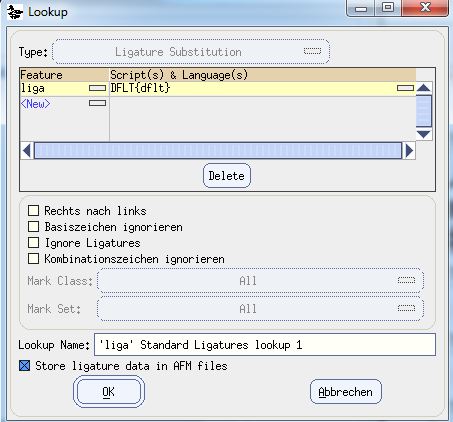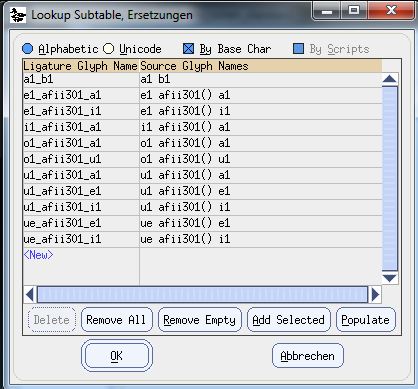
Frage zu Ligaturen/Ersetzungen
Aber wo wir und hier für die Wiederbeschäftigung unterbeschäftigter Buchstaben einsetzen. auch das y hatte damals - also in der Zeit mit dem u/v-Regel-Ding weit mehr Verwendung. Damals wurde es ja für den Ungerundeter geschlossener Hinterzungenvokal verwendet, der dann ber auch als 2. Teil des diphthonge ei auftaucht, und demzufolge konsequent ey geschrieben wurde.
Das ist kein sprachliches Problem, sondern ein rein Orthografisches.
Das die deutsche Sprache überhaupt noch in der Lage ist, solche einfachen Wortverbindungen aufzubauen, sollte als eine Gabe gesehen werden, die in vielen westlichen Sprachen schon verloren gegangen ist.
Zumindest in den anderen germanischen Sprachen funktioniert das genauso gut wie im Deutschen. Im Englischen verhȧlt es sich debei nur so, dass die verbundenen Wörter nicht auch noch verbunden geschrieben werden. Abgesehen von diesem orthographischen Unterschied funktioniert aber die englische Wortverbindung genau gleich wie im Deutschen.
Warum "Wachs" nicht "Wax" geschrieben wird (wie es auch der Aussprache entspricht), versteh ich nun überhaupt nicht,... wenn nun schon ein x im Alphabet vorhanden ist... sollte dieses auch genutzt werden.
Bei uns ist die Aussprache mit CH und S völlig normal.
nun habe ich das Problem, dass die Schriftdatei die Ligatur-Funktionen nicht auf die Schriftzeichen im "Private Use Zone" bezieht.
Die Ersetzungen an sich funktionieren, jedoch nur, wenn "lateinische Buchstaben" ersetzt werden sollen;
Nun befinden sich jedoch die Schriftzeichen - einschließlich aller Grundlaute - im privaten/ unbelegten Unicodebereich. Über ein eigens hierfür kreiertes zweites deutsches Tastaturlayout (für Windoof) können die Schriftzeichen eingegeben werden. Die Namen der einzelnen Glyphen im "PUA" der Schriftdatei sind die lateinischen Entsprechungen, wobei über eine angehängte Ziffer eine Verwechslung mit den Namen der Gylphen im Unicode-Block "Latin" ausgeschlossen werden soll.
beispielsweise wird der "f"-Laut in der "Private Use Zone" als "f1" bezeichnet (um eine Verwechslung mit dem lateinischen "f" auszuschließen).
Problem ist nun, dass die Ersetzungen (beispielsweise in Abiword) nicht funktionieren; aber sehr wohl, wenn ich meinen ersten Entwurf nehme, wo sich alle Schriftzeichen noch im lateinischen Unicod-Block zugeordnet befinden.
Ich denke, das Problem hat nichts mit dem zweiten Tastaturlayout zu tun, sondern ist ein Zuordnungsproblem im Schriftfont; vielleicht muss noch irgendwo angegeben werden, auf welchen Bereich sich die "Ligaturen" (bzw. allg. Ersetzungen) beziehen?...
Anbei drei Bilder zu den von mir betätigten Optionen...
Im 3. Bild sind die gegenwärtigen Ersetzungen zu sehen (der große Rest folgt später).
Die erste "Ligatur" ist die "ab"-Silbe, die nachfolgenden Reihen sind verschiedene Zwielaute (für diverse Dialekte), die mithilfe des Nullbreitenzeichen über die Tastatur ermöglichst werden sollen.
Allg. zur Schrift: das "Projekt" ist eine Lautschrift für die Deutsche Sprache, bzw. eine, die alltagstauglich, d.h. möglichst logisch- und einfach strukturiert ist, und dennoch eindeutig und exakt die Wörter so darstellt, wie diese auch ausgesprochen werden.
auch existieren für ALLE Laute (bsp. "ng", "ch", "sch", "pf" usw..) eindeutige Schriftzeichen, weshalb die Wörter extrem stark entschlackt, kürzer geschrieben werden als im lateinischen Alphabet.
Insgesamt sind es 47 Grundlaute / Grundbuchstaben. Diese sind dann noch systematisch untereinander kombiniert:
1. die Konsonanten untereinander, z.B. "tsch", "schr", "schp" (wie in "sp-ielen"), ngk (wie in "Da-n[g]k), "fr", "lz", "nft" (wie in Zuku-nft") usw...)
(insgesamt ca. 300 solcher "Verknüpfungen"; aber diese sind sehr sehr sehr leicht zu merken, da extrem systematisch, sodass tatsächlich nur um die 100 neue Zeichen erstellt werden müssen);
2. Silben (aber nur "Vokal oder Zwielaut + Konsonant" und umgekehrt) zB. "ab" oder "ba", "deu" oder "eud";
das ergeben ca. 900 Kombinationen (wobei hier ebenfalls immer horizontal gespiegelt wird; z.B. bei ab -> ba; weshalb es keine große Arbeit ist, die ganzen Kombinationen zu erstellen, weil noch der Umstand hinzukommt, dass sehr viel gedreht und gespiegelt wird, um unterschiedliche Vokale darzustellen; das gleiche trifft auch auf die Konsonanten zu z.B. tsch -> scht (Schriftzeichen wird einfach gespiegelt).
Wenn ich Bug 31821 – Writer ignores OpenType ligatures richtig verstehe, so ist das Problem behoben worden und es steht eine Version von LibreOffice bevor, die das OpenType Layout umsetzt.
...und das sieht sehr danach aus, wenn das da dann nicht auch so eine halbherzige Sache wie in MS Office wird, dann werde ich mir die Sache mit den Operntype-Funktionsschriften noch mal anders bedenken. Und das dann auch in allen Schriftarten, denn gerade in Schreibschrift-Fonts ließe sich da einiges umsetzen, wenn es dann auch für die Nutzer einsetzbar wird.